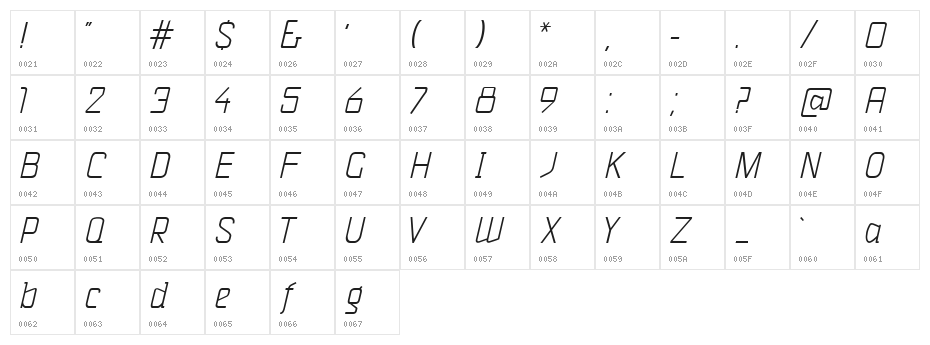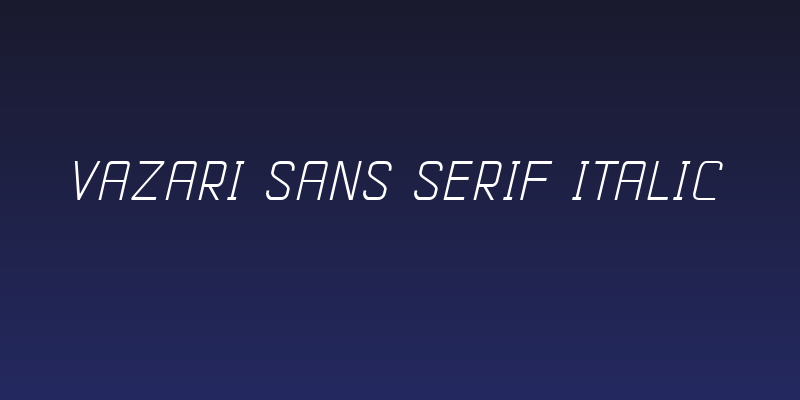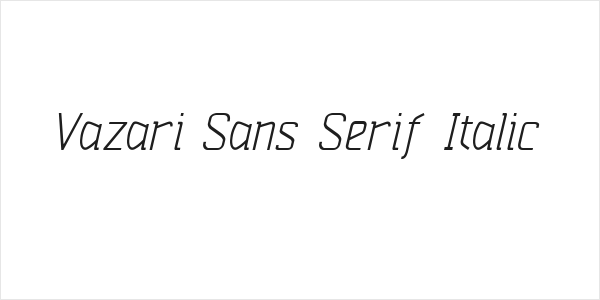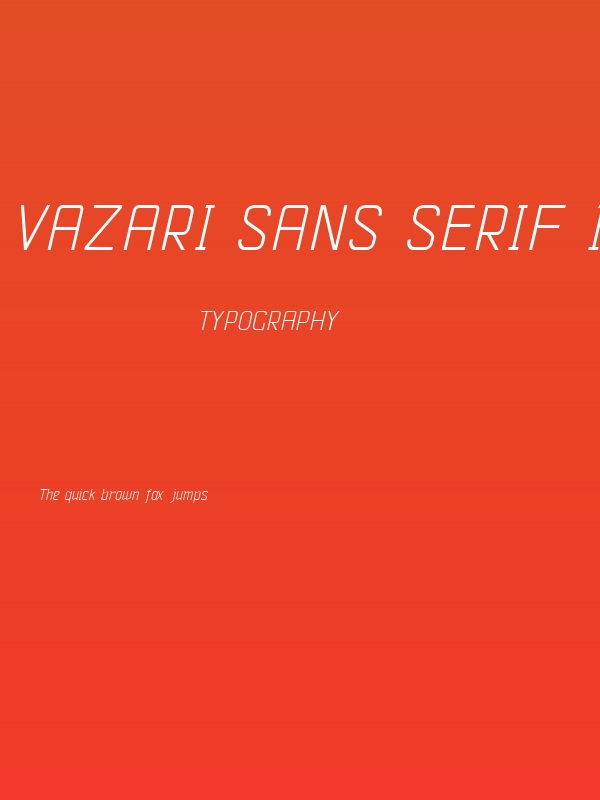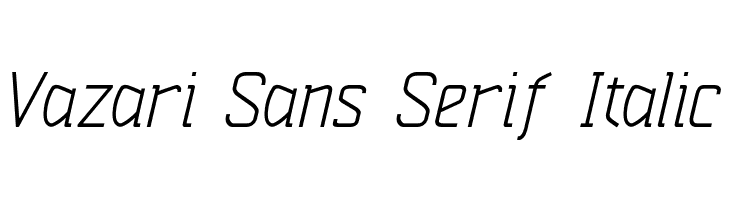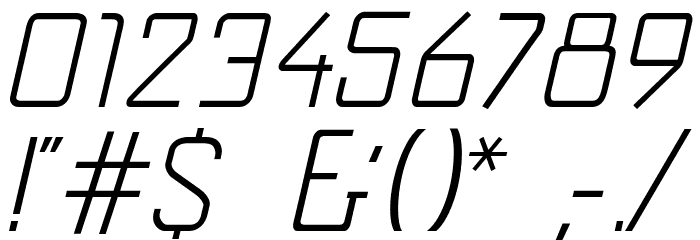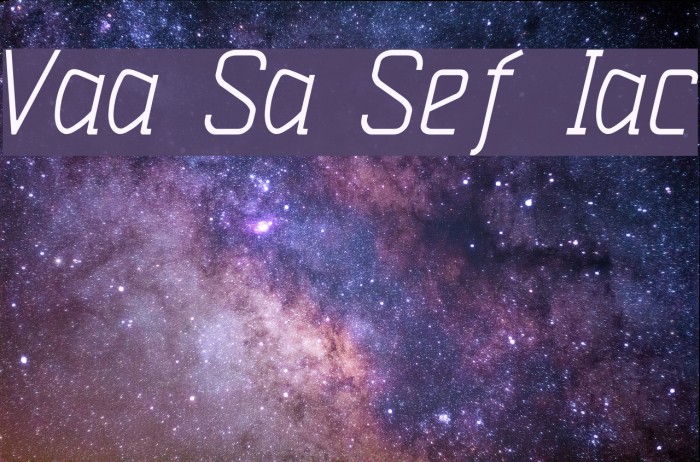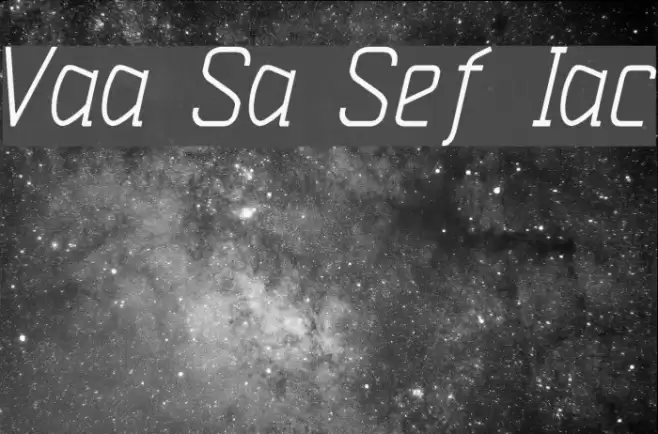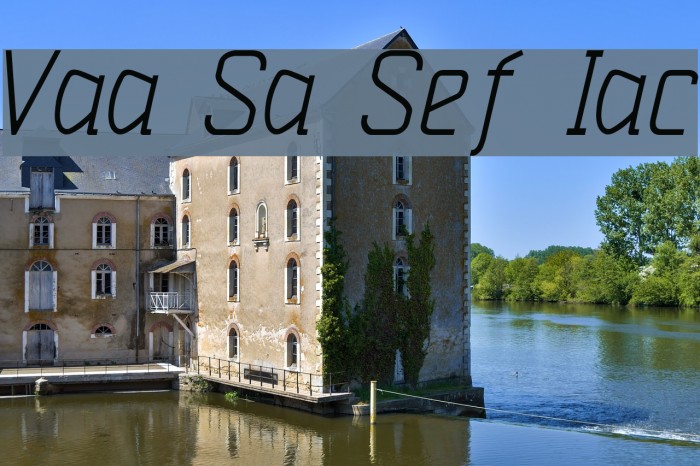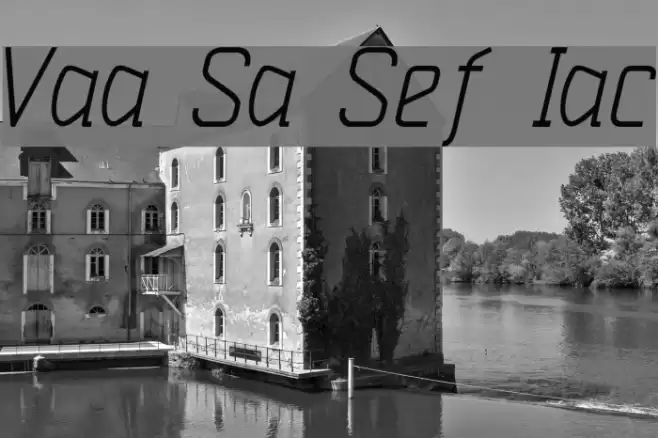
Vazari Sans Serif Italic Font
| 名前 | Vazari Sans Serif Italic |
| ウェイト | Italic |
| おすすめプロジェクト | Ideal for branding, advertising, digital interfaces, and editorial design where a modern and dynamic look is desired. |